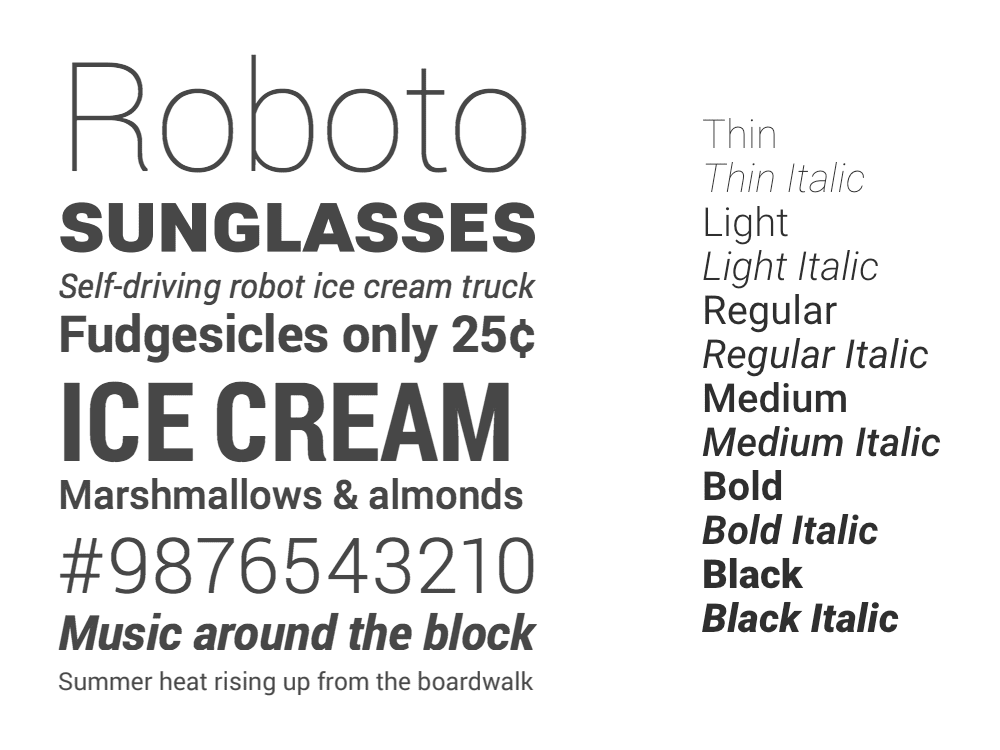
Một quy cách phông chữ mới có thể giảm đáng kể kích thước tệp phông chữ
Trong bài viết này, bạn sẽ khám phá phông chữ biến đổi, những lợi ích mà phông chữ này mang lại và cách sử dụng chúng trong công việc của bạn. Trước tiên, hãy xem lại cách hoạt động của kiểu chữ trên web và những điểm mới lạ mà phông chữ có thể thay đổi mang lại.
Giới thiệu
Các nhà phát triển thường dùng lẫn lộn thuật ngữ phông chữ và kiểu chữ. Tuy nhiên, có một điểm khác biệt: Kiểu chữ là thiết kế hình ảnh cơ bản có thể tồn tại trong nhiều công nghệ sắp chữ khác nhau, còn phông chữ là một trong những cách triển khai này, ở định dạng tệp kỹ thuật số. Nói cách khác, kiểu chữ là thứ bạn nhìn thấy, còn phông chữ là thứ bạn sử dụng.
Một khái niệm khác thường bị bỏ qua là sự khác biệt giữa kiểu chữ và họ chữ. Kiểu là một kiểu chữ đơn lẻ và cụ thể, chẳng hạn như In đậm và nghiêng, còn họ là toàn bộ tập hợp các kiểu.
Trước khi có phông chữ biến đổi, mỗi kiểu chữ được triển khai dưới dạng một tệp phông chữ riêng biệt. Với phông chữ có thể thay đổi, tất cả kiểu chữ đều có thể nằm trong một tệp duy nhất.
Thách thức đối với nhà thiết kế và nhà phát triển
Khi tạo một dự án in, nhà thiết kế sẽ phải đối mặt với một số hạn chế, chẳng hạn như kích thước thực của bố cục trang, số lượng màu mà họ có thể sử dụng (được xác định bởi loại máy in sẽ được sử dụng), v.v. Nhưng họ có thể sử dụng bao nhiêu kiểu chữ tuỳ thích. Điều này có nghĩa là kiểu chữ của phương tiện in thường phong phú và tinh tế, để trải nghiệm đọc thực sự thú vị. Hãy nghĩ về lần gần đây nhất bạn thích thú khi duyệt xem một tạp chí hay.
Nhà thiết kế và nhà phát triển web có những hạn chế khác với nhà thiết kế bản in, một trong số đó là chi phí băng thông liên quan đến các thiết kế của chúng tôi. Đây là một điểm khó khăn đối với trải nghiệm kiểu chữ phong phú hơn, vì chúng có chi phí. Với phông chữ web truyền thống, mỗi kiểu được sử dụng trong thiết kế của chúng tôi đều yêu cầu người dùng tải một tệp phông chữ riêng biệt, điều này làm tăng độ trễ và thời gian hiển thị trang. Chỉ bao gồm các kiểu Chữ thường và Chữ đậm, cộng với các kiểu chữ nghiêng tương ứng, có thể chiếm đến 500 KB hoặc hơn dữ liệu phông chữ. Đây là trước khi chúng ta xử lý cách phông chữ được hiển thị, các mẫu dự phòng mà chúng ta cần sử dụng hoặc các tác dụng phụ không mong muốn như FOIT và FOUT.
Nhiều bộ phông chữ cung cấp nhiều kiểu dáng hơn, từ độ đậm Thin đến Black, chiều rộng hẹp và rộng, nhiều chi tiết về kiểu dáng và thậm chí cả thiết kế dành riêng cho kích thước (được tối ưu hoá cho cỡ chữ lớn hoặc nhỏ). Vì bạn sẽ phải tải một tệp phông chữ mới cho mỗi kiểu (hoặc tổ hợp kiểu), nên nhiều nhà phát triển web chọn không sử dụng các chức năng này, làm giảm trải nghiệm đọc của người dùng.
Cấu trúc của phông chữ biến đổi
Phông chữ có thể thay đổi giúp giải quyết những thách thức này bằng cách đóng gói các kiểu vào một tệp duy nhất.
Cách này hoạt động bằng cách bắt đầu với một kiểu chữ trung tâm hoặc "mặc định", thường là kiểu chữ "Regular" (Thông thường) – một kiểu chữ La Mã thẳng đứng với trọng lượng và chiều rộng điển hình nhất, phù hợp nhất với văn bản thuần tuý. Sau đó, kiểu chữ này được kết nối với các kiểu chữ khác trong một dải liên tục, được gọi là "trục". Trục phổ biến nhất là Độ đậm, có thể kết nối kiểu mặc định với kiểu In đậm. Mọi kiểu chữ riêng lẻ đều có thể nằm dọc theo một trục và được gọi là "thể hiện" của phông chữ biến đổi. Một số trường hợp được nhà phát triển phông chữ đặt tên, ví dụ: vị trí 600 của trục Độ đậm được gọi là Bán đậm.
Phông chữ có thể thay đổi Roboto Flex có 3 kiểu cho trục Độ đậm. Kiểu Chữ thường nằm ở giữa, và có hai kiểu ở hai đầu đối diện của trục, một kiểu nhẹ hơn và một kiểu nặng hơn. Trong số này, bạn có thể chọn trong số 900 phiên bản:
Nhà phát triển phông chữ có thể cung cấp một bộ gồm nhiều trục. Bạn có thể kết hợp các thành phần này vì chúng đều có cùng kiểu mặc định. Roboto có 3 kiểu trong trục Chiều rộng: kiểu Thông thường nằm ở giữa trục và 2 kiểu hẹp hơn và rộng hơn nằm ở mỗi đầu. Các trục này cung cấp tất cả các chiều rộng của kiểu Regular và kết hợp với trục Weight để cung cấp tất cả các chiều rộng cho mọi độ đậm.
Điều này có nghĩa là có hàng nghìn kiểu chữ! Điều này có vẻ hơi thừa, nhưng chất lượng của trải nghiệm đọc có thể được nâng cao đáng kể nhờ sự đa dạng của các kiểu chữ này. Và nếu không bị ảnh hưởng đến hiệu suất, nhà phát triển web có thể sử dụng một vài hoặc nhiều kiểu tuỳ ý – điều này phụ thuộc vào thiết kế của họ.
In nghiêng
Cách xử lý chữ in nghiêng trong phông chữ có thể thay đổi rất thú vị, vì có 2 cách tiếp cận khác nhau. Các kiểu chữ như Helvetica hoặc Roboto có đường viền tương thích với nội suy, vì vậy, các kiểu chữ La Mã và chữ nghiêng có thể được nội suy giữa các kiểu chữ này và bạn có thể dùng trục Độ nghiêng để chuyển từ kiểu chữ La Mã sang chữ nghiêng.
Các kiểu chữ khác (chẳng hạn như Garamond, Baskerville hoặc Bodoni) có đường viền chữ cái La Mã và chữ nghiêng không tương thích với nội suy. Ví dụ: đường viền thường xác định chữ "n" viết thường trong kiểu chữ La Mã không khớp với đường viền dùng để xác định chữ "n" viết thường trong kiểu chữ nghiêng. Thay vì nội suy một đường viền sang đường viền khác, trục Italic sẽ chuyển đổi từ đường viền Roman sang đường viền Italic.